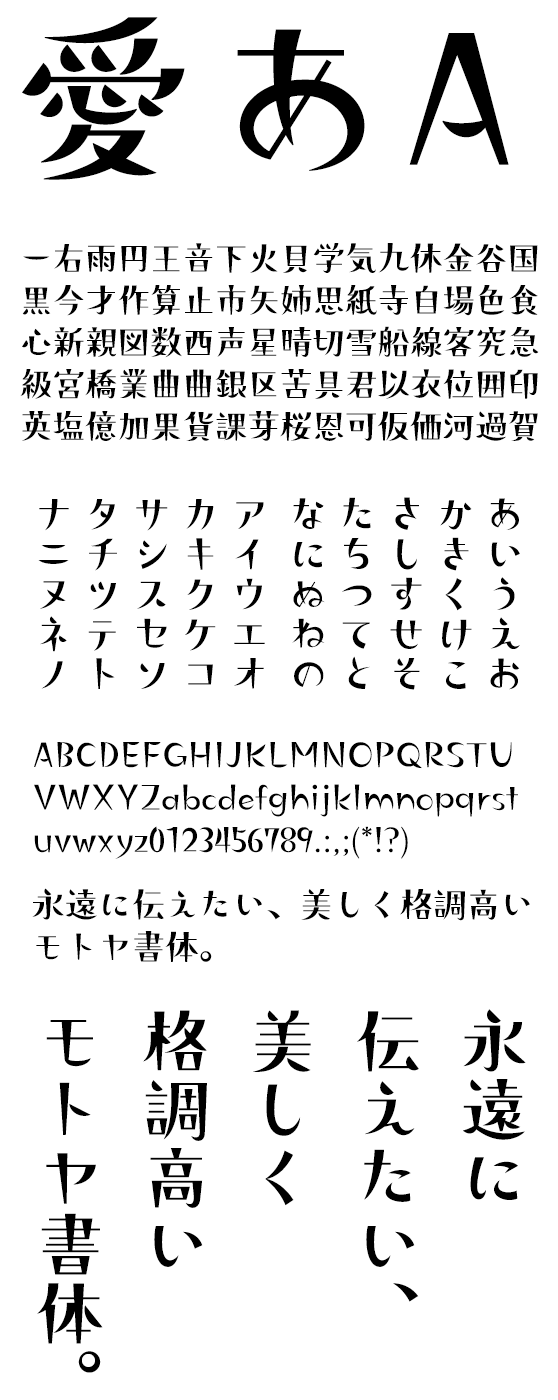
モトヤワルツ5 LiteN
MotoyaWaltzLiteN-W5
ゲームやコミックといったポップカルチャーでの使用を想定して開発されました。月の満ち欠けをモチーフにした特徴的なアクセントと、全体的に少しいびつなバランスが、レトロな雰囲気と共に独特のリズム感をかもし出し、そのキャッチーな表情の中にダークな印象をも感じさせる、不思議な味わいの書体です。